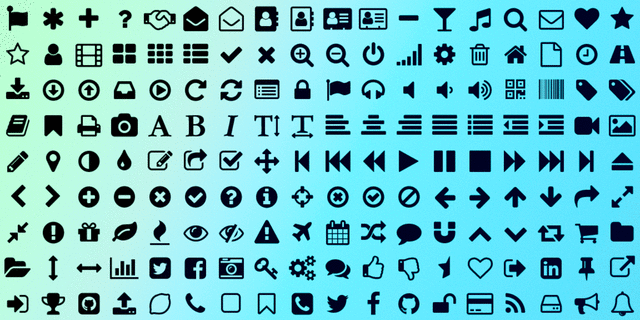
Бесплатный веб шрифт, состоящий из простых векторных пиктограмм. Содержит 675 иконок + пакет CSS-инструментов. Это самые распространенные символы для интерфейса сайтов, магазинов, настольных и мобильных приложений, а также городские знаки, и логотипы популярных социальных сетей. Font Awesome пригодится в веб-дизайне, дизайне приложений и даже в полиграфии, например для фирменной документации, визиток, рекламы. Шрифт разработан Дейвом Генди в 2016 году и распространяется по лицензии SIL OFL 1.1 для шрифта и MIT License для CSS-пакета: http://fontawesome.io/license.
Ассоциации c семейством Font AwesomeКачества и характер:
простой, городской, современный, глобалистичный, глобализированный, космополитичный, международный, удобный, стандартный, нейтральный, деловой
— Особенности семейства Font AwesomeХит десятилетия:
Хит 2010-х Этот шрифт в логотипах:
Facebook, Twitter, Instagram, Google, Vkontakte, Visa, Windows, MacOS, Linux, Skype, PayPal, YouTube